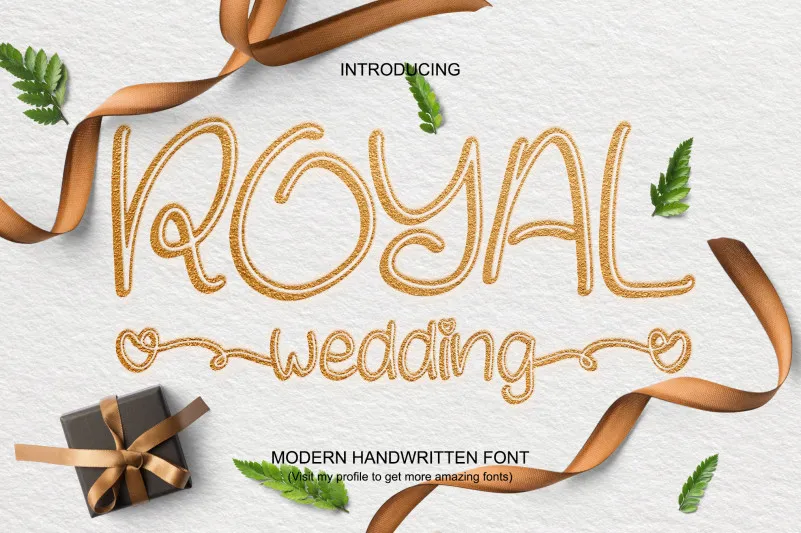
Royal Wedding Font
Esta é uma fonte script luxuosa e delicada, onde os caracteres dançam ao longo do baseline. Ela oferece uma vasta gama de símbolos e swashes que você pode acessar facilmente devido à sua codificação PUA. Ideal para aniversários de casamento ou qualquer outro evento especial, a Royal Wedding Font é perfeita para quem busca um estilo elegante e sofisticado em suas criações. Seja para títulos grandiosos ou pequenos detalhes, esta fonte trará ao seu projeto uma elegância única que complementa perfeitamente sua mensagem. Esse recurso gráfico não apenas torna o texto mais atraente e interessante, mas também oferece flexibilidade na criação de qualquer tipo de layout, desde cards de convite até designs para jornalismo e marketing. Com a Royal Wedding Font do Designer welovefont, você terá todas as ferramentas necessárias para personalizar seu projeto e criar algo verdadeiramente especial.